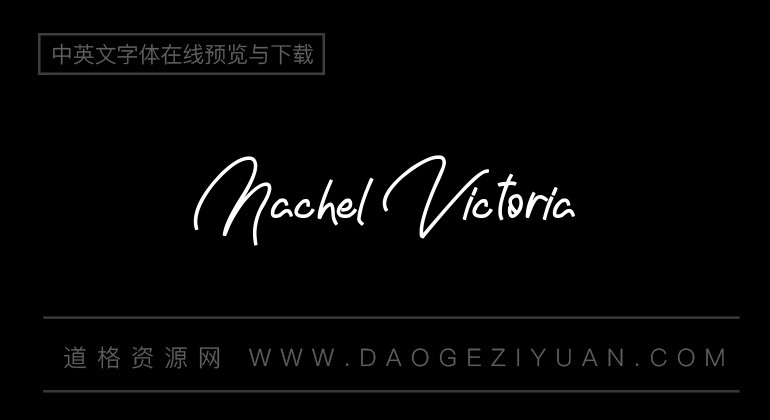
Nachel Victoria
? Nachel Victoria 字体是一款细腻的花体字体,它具有古典的风格,让字体看起来更加优雅,更有深度。Nachel Victoria 字体的字体粗细和轮廓线条都非常精细,可以让文字看起来更加精致。此外,Nachel Victoria 字体还有一些可爱的小装饰,可以让文字看起来更加有趣。总之,Nachel Victoria 字体是一款非常优秀的花体字体,可以用于各种文档和设计,为文字增添优雅的气息。
Nachel Victoria是一款非常不错的手写艺术字体,具有很好的视觉感,适合于文化类的宣传设计、商业类品牌的广告和产品包装设计以及个性化文字排版等较多场景。